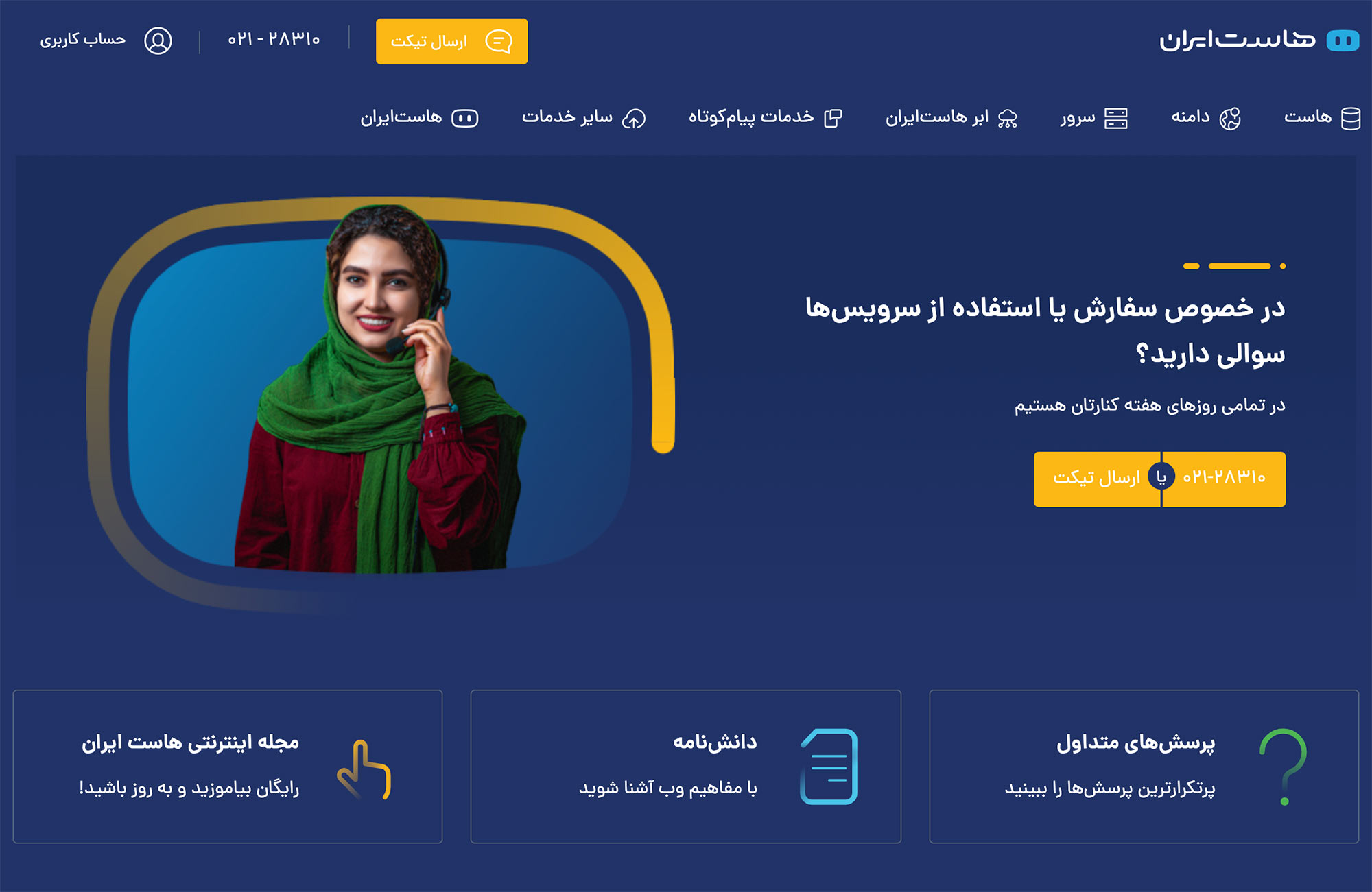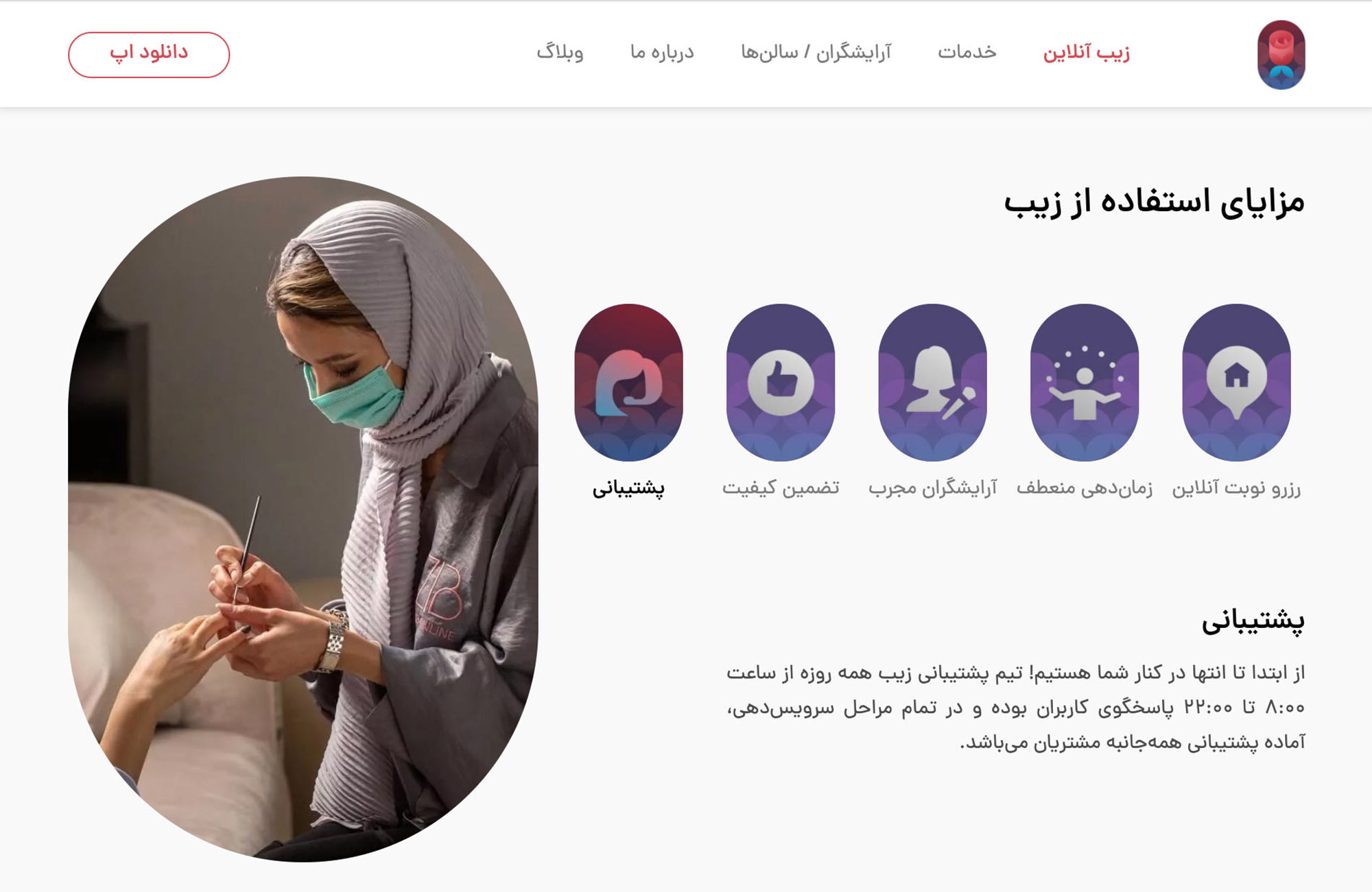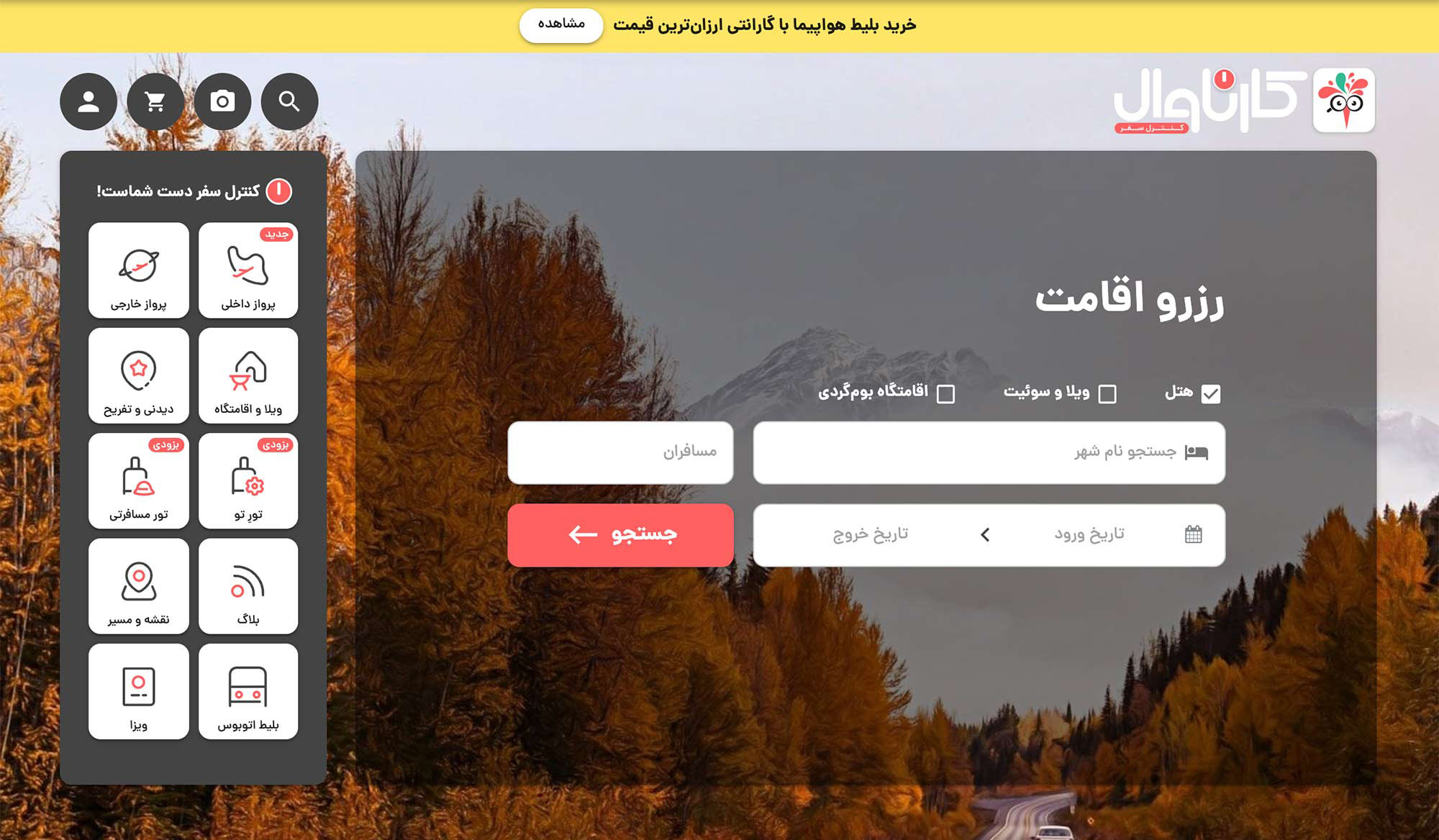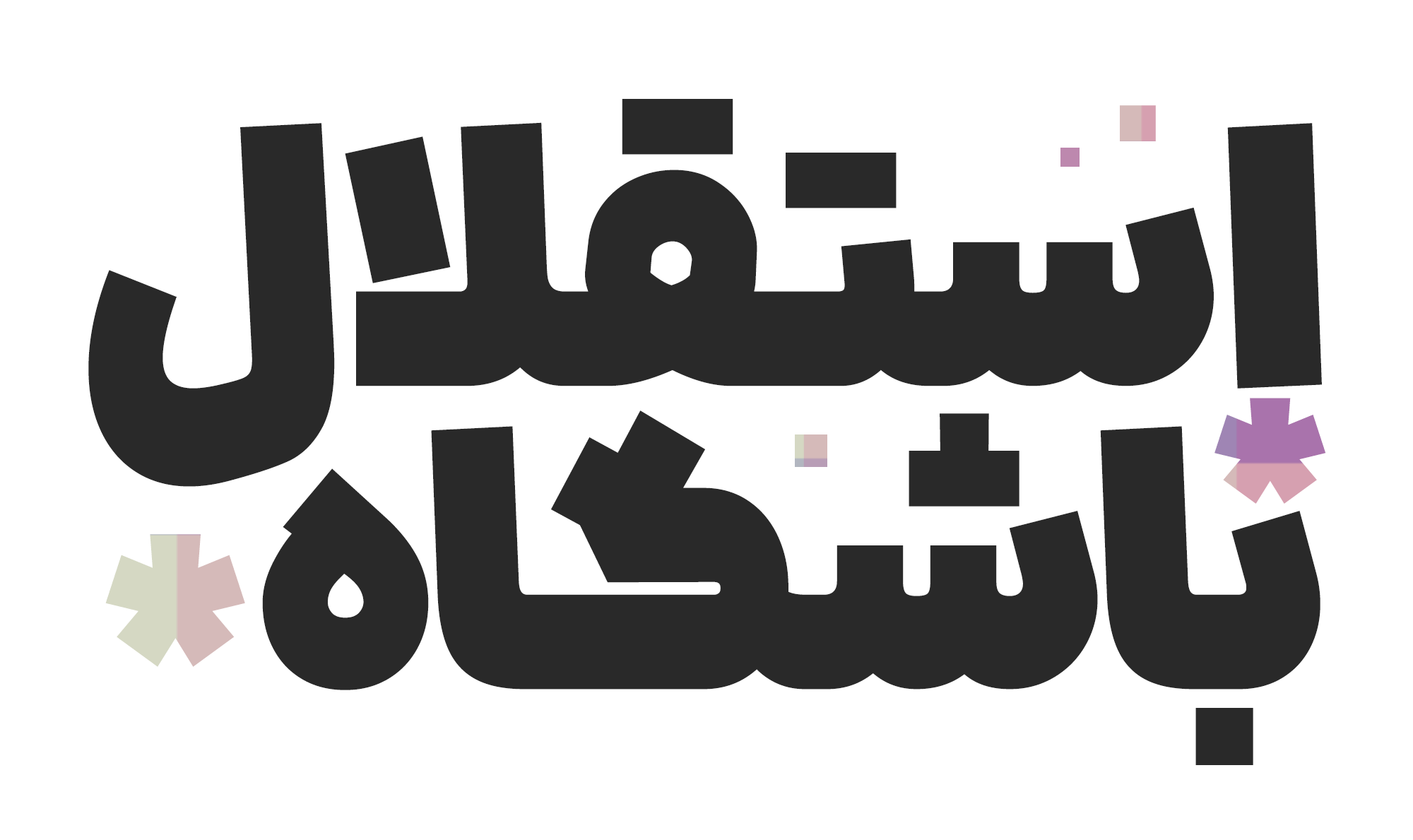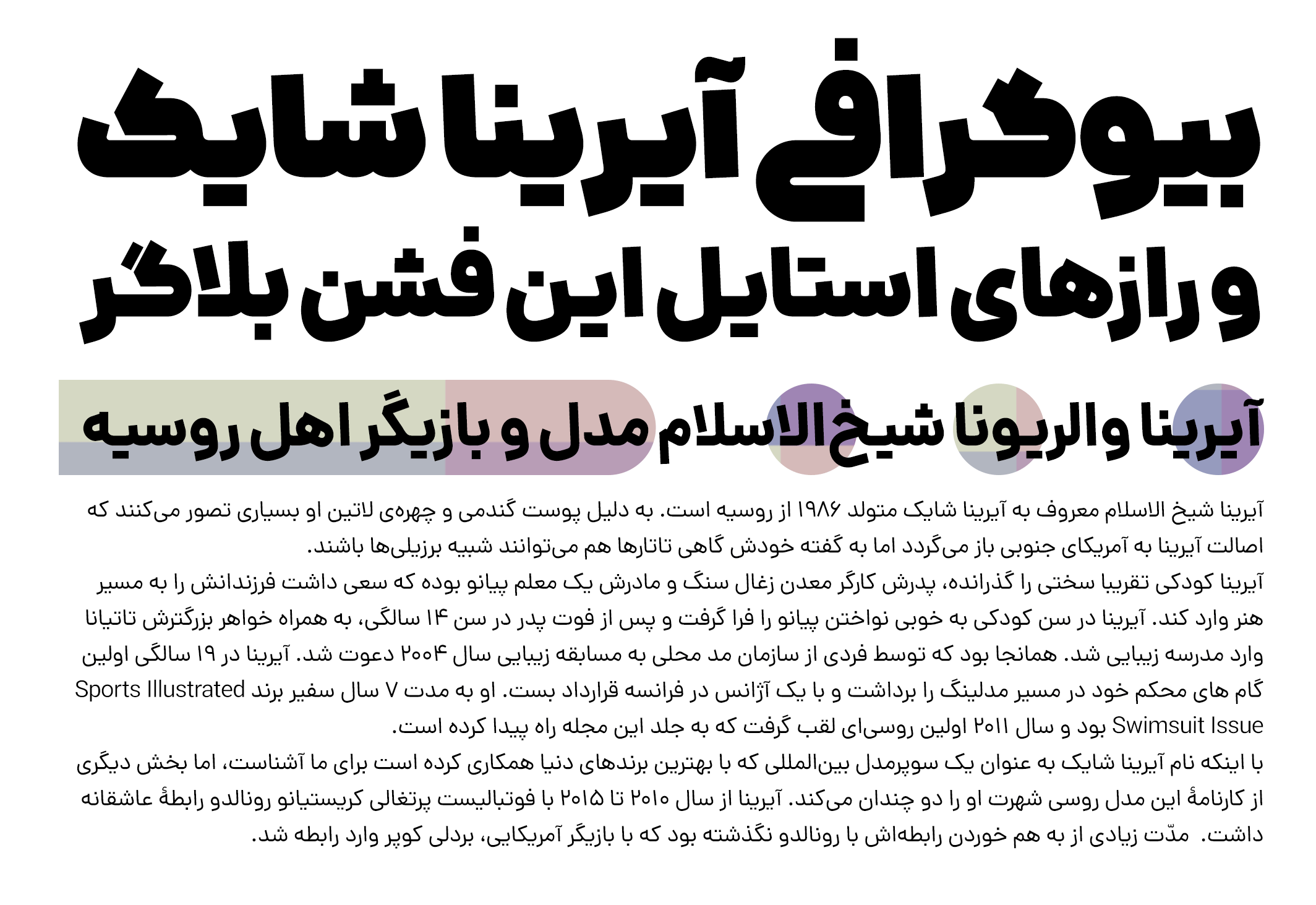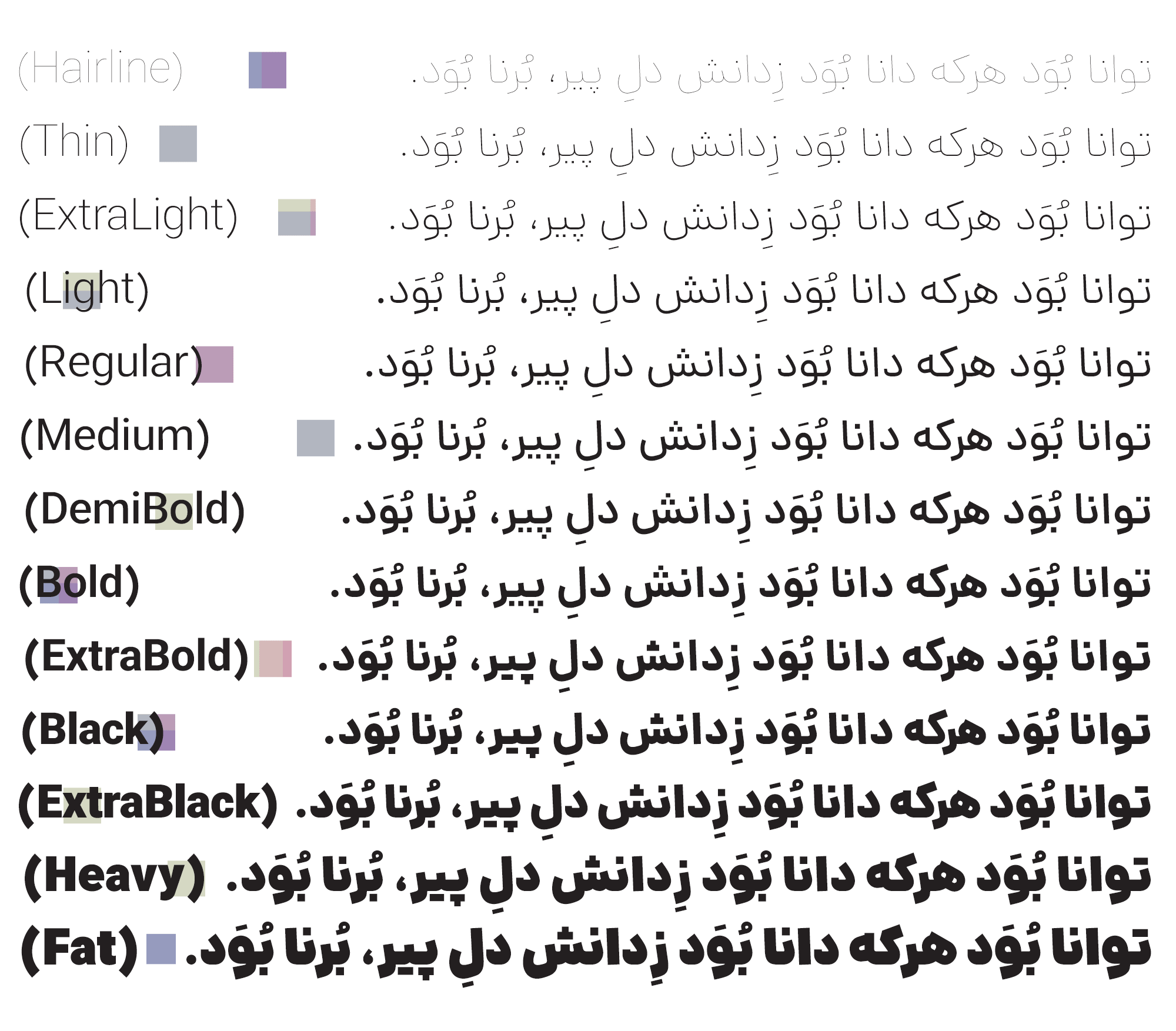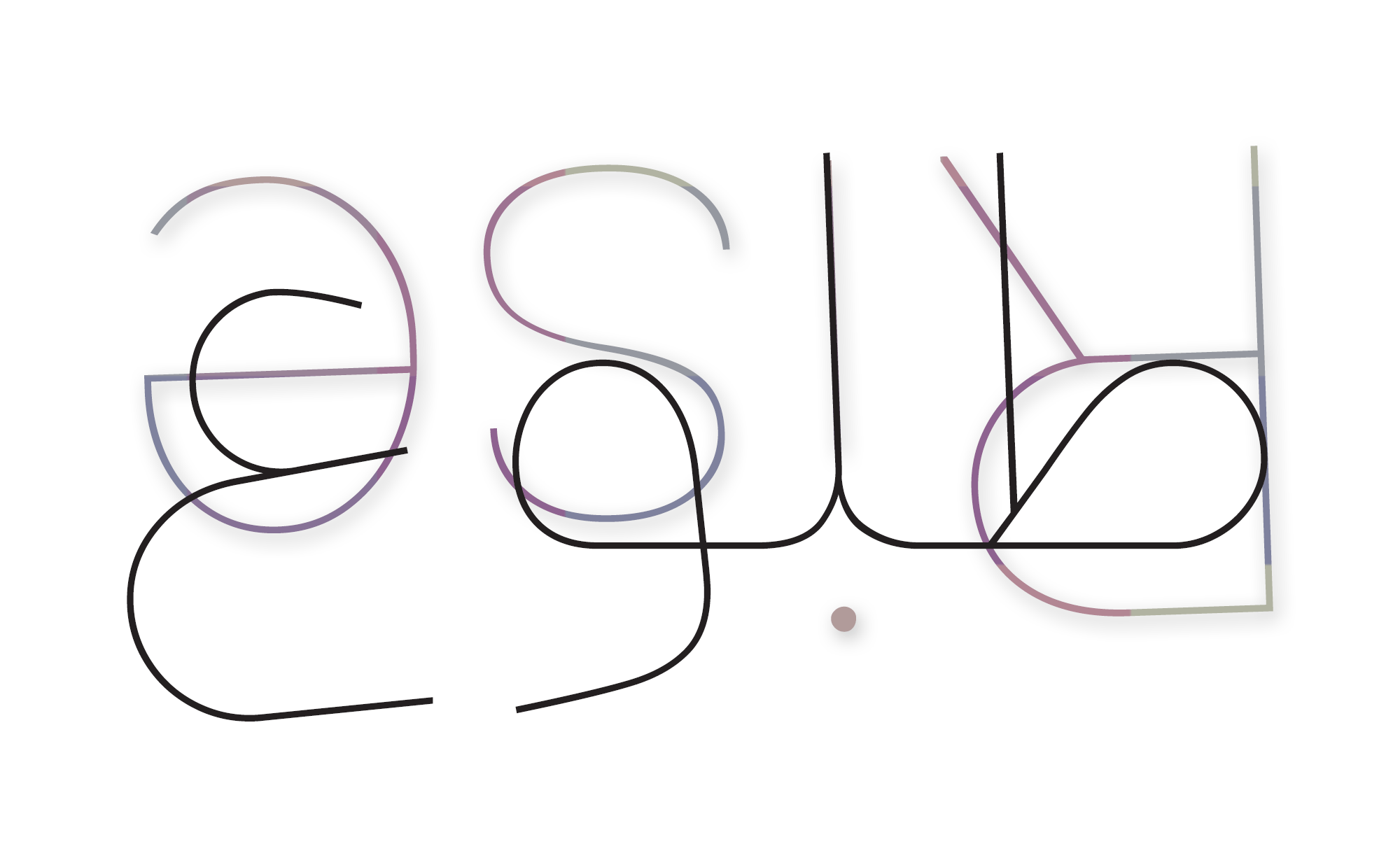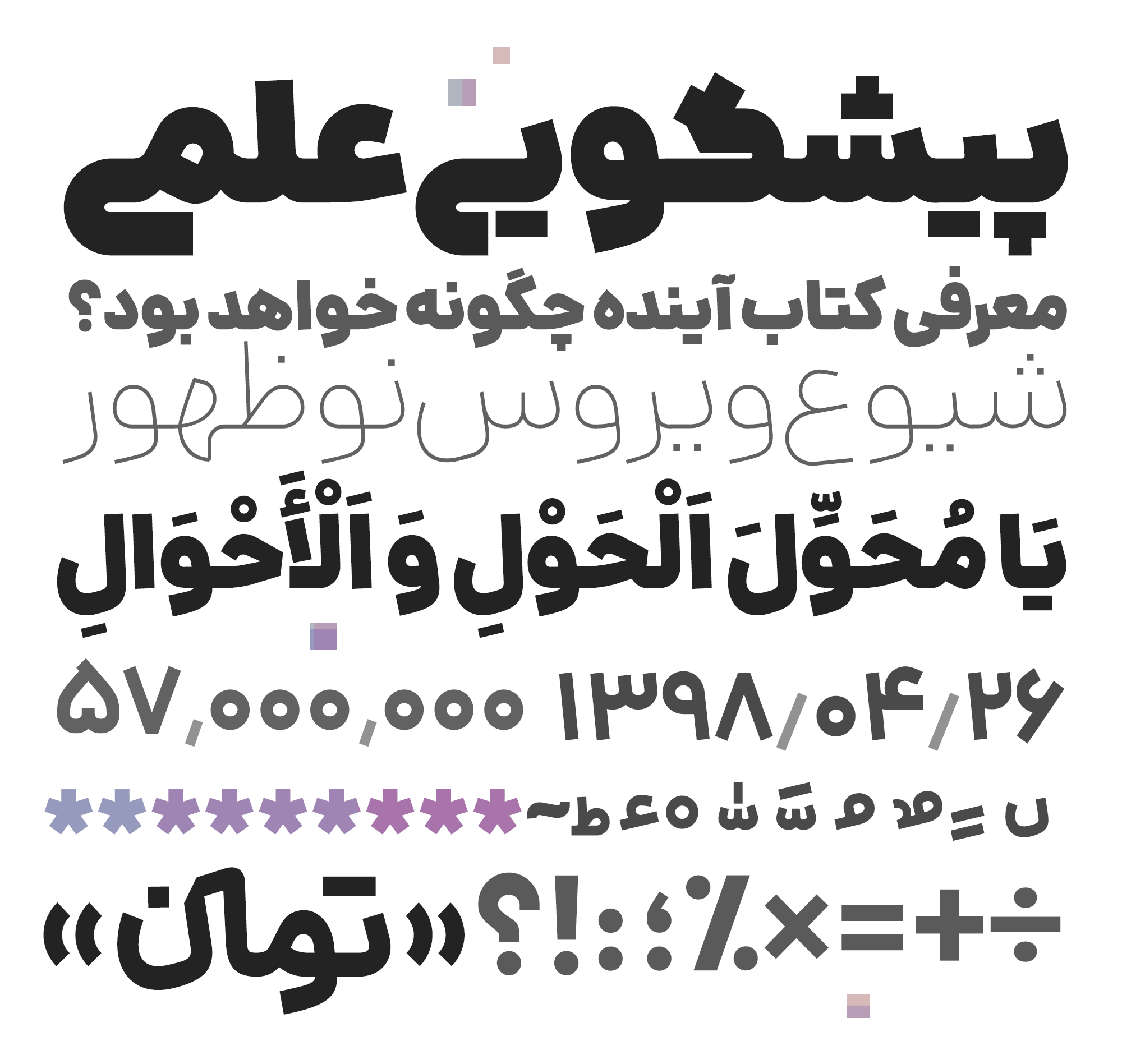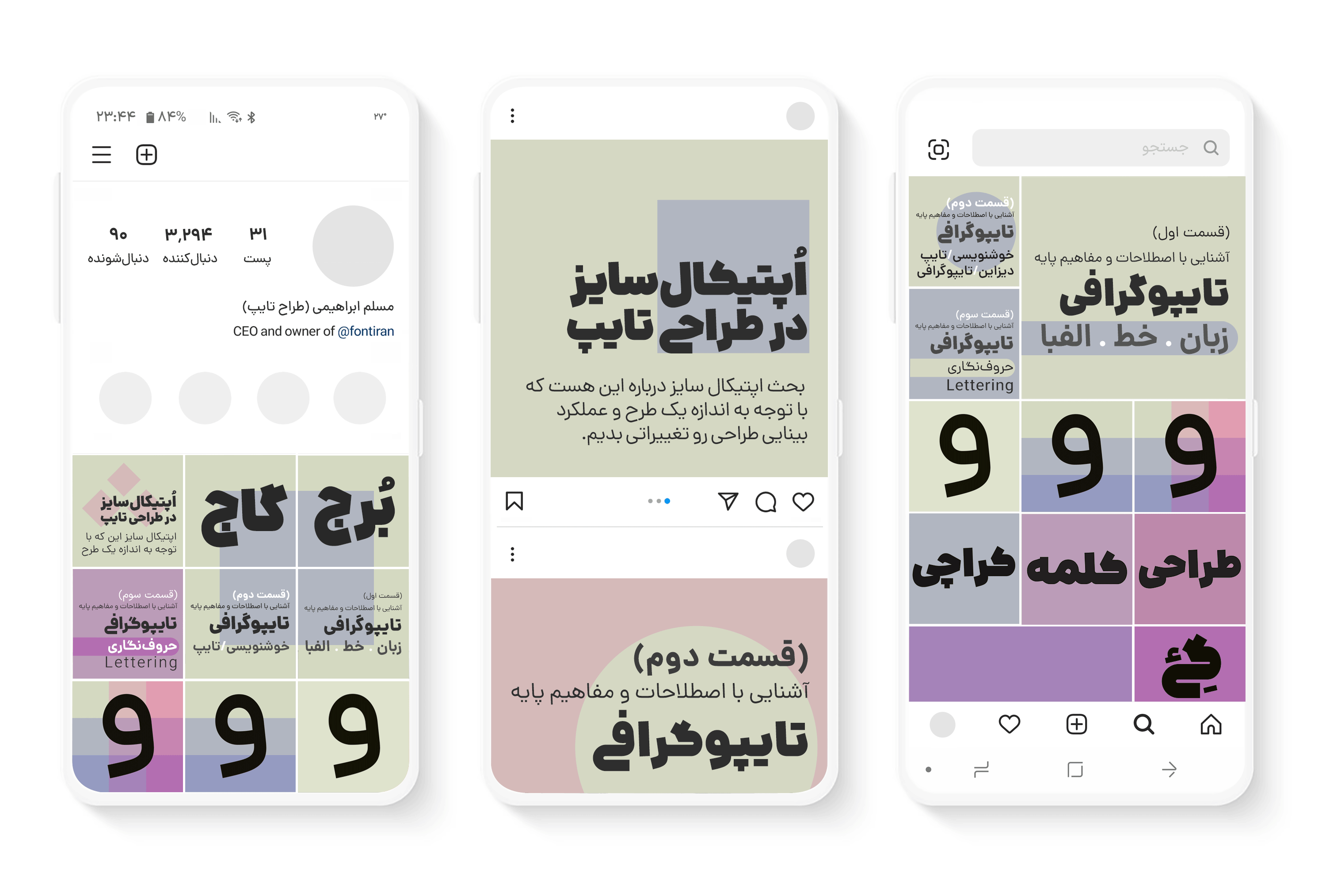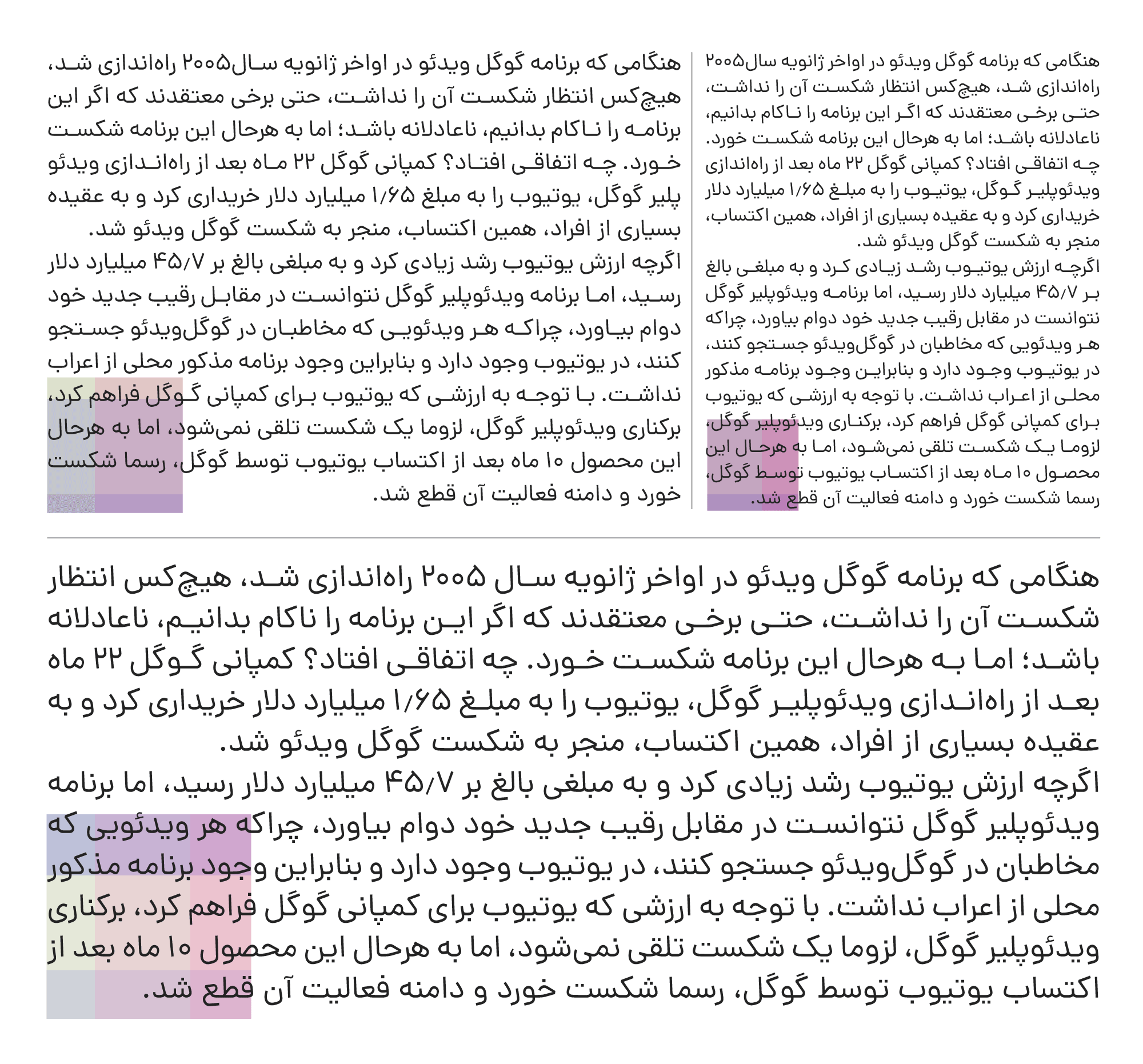
فونت دانا
فونت دانا تلاشی است برای خلق یک تایپ‌فیس هندسی و نزدیک به خط نسخ.
هندسی بودن باعث می‌شود فونت دانا مدرن و معاصر به نظر برسد و وفاداری به شیوه نسخ باعث می‌شود در اندازه ریز و نوشته‌های طولانی خوانایی آن حفظ شود.
فونت دانا نخستین بار در خرداد ۱۳۹۸ منتشر شد و همواره در میان طراحان محصول محبوب بوده است.
بسیاری از برند‌ها و کسب و کارهای جدید برای دستیابی به طراحی مدرن و معاصر از فونت دانا استفاده کرده‌اند. در انتهای این صفحه می‌توانید تعدادی از این طراحی‌ها را ببینید.
زیبایی در کمال نهان است
هندسه موجود در حروف فونت دانا با ترکیب خط مستقیم و دایره شکل گرفته است و بجز در موارد بسیار کم سعی شده است از منحنی آزاد استفاده نشود.
برای حفظ حس و حال خوشنویسی و پویایی بیشتر راستای عمودی در فونت دانا دارای اندکی زاویه است و از خط عمودی در ترسیم حروف استفاده نشده است.
خانواده سیزده‌تایی
فونت دانا در نسخه قبلی دارای ۱۰ وزن بود که در بازسازی جدید ۳ وزن سنگین به آن اضافه شده است. بنابراین اکنون ۱۳وزن در دسترس است.
وریبل فونت دانا
بیشترین کاربرد فونت متغیر در طراحی وبسایت بوده است. یک فایل فونت برای همه‌ی نیازها.
وریبل فونت دانا تنها ۱۲۰ کیلو بایت حجم دارد؛ شامل ۱۳ وزن، اعداد فارسی و … این برای افزایش سرعت بارگزاری وبسایت شما و زیباتر شدن آن بهترین انتخاب است.
در اولین نسخه خود که در خرداد ۱۳۹۸ منتشر شد دارای متغیرهای متعددی بود. وریبل فونت و کار با متغیرهای گوناگون هیجان انگیز بود و این فونت تا حد زیادی تحت تاثیر این تکنولوژی جدید قرار گرفت. اما بعضی از متغیرها بسیار کم کاربرد بود. بنابراین ما در نسخه جدید فونت دانا از آنها صرف نظر کردیم تا از پیچیدگی فونت کم کنیم و در عوض کیفیت طراحی و ساخت را افزایش دهیم.
در این نسخه از فونت دانا دو وریبل تغییر وزن و کشیدگی وجود دارد.
Weight : این متغیر وزن (ضخامت) نوشته را تعیین می‌کند که حداقل آن 10 معادل وزن Hairline و حداکثر آن 990 معادل وزن fat است.
Kashidah : این متغیر می‌تواند در کلمات کشیدگی ایجاد کند که مقدار آن از صفر تا 100 است.
باریک‌تر از مو!
نازک‌ترین وزن در خانواده فونت دانا (Hireline) بیشتر از هر فونت فارسی که تا کنون دیده‌ایم نازک و ظریف است. وزن‌های بسیاز نازک کاربرد نمایشی دارند و مناسب استفاده در اندازه‌های بزرگ هستند و نه متن ریز.
وقتی نوشته آن قدر نازک باشد که حداقل سیاهی را ایجاد کند، سفیدی و فضای خالی بر طرح حاکم می‌شود. این سبک طراحی دارای حس و حال مینیمال، آرام و ظریف است.
بالاتر از سیاهی!
با توجه به کاربرد زیاد فونت‌های سنگین در طراحی پوسترها ویژه موبایل (کاورها و استوری‌های اینستاگرام)، حروف در فونت دانا در حدی ضخیم طراحی شده است که قابل خواندن در اندازه کوچک باشد.
فونت‌های سنگین در کنار دیگر وزن‌ها خودنمایی می‌کنند و دارای خاصیت تبلیغاتی پر قدرت هستند.